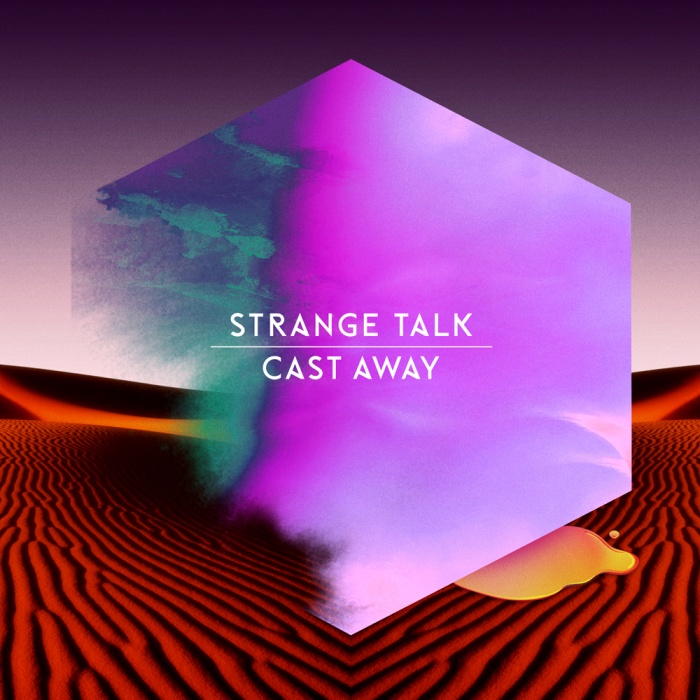
Scheint ja gerade beliebt zu sein, den "A"-Balken so quer zu stellen .. Das spitze "A" und das "G" im Schriftzug von Strange Talk gefallen mir aber besser als bei der Diamonds.